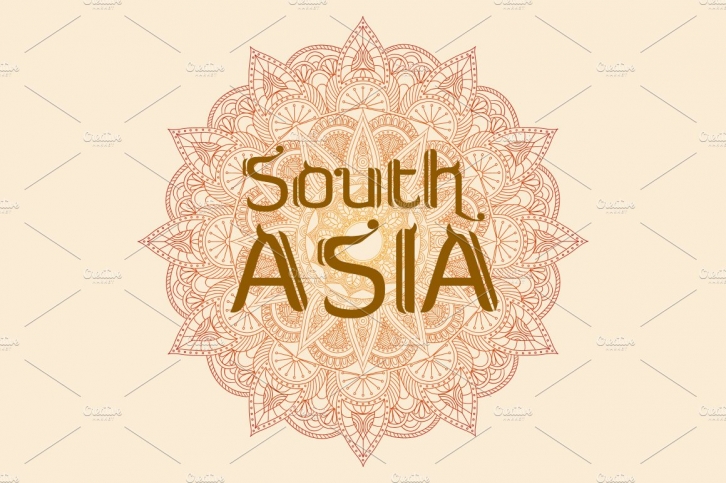
English: Inspired by the two cultures of Indonesia, puppets and ancient Javanese script.
Indonesia: Terinspirasi dari 2 budaya Indonesia, wayang (tokoh pewayangan Semar di Punakawan) dan aksara jawa kuno.
Terciptalah font unik ini dan sangat ekslusif.